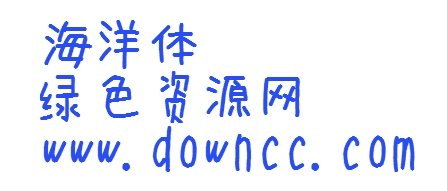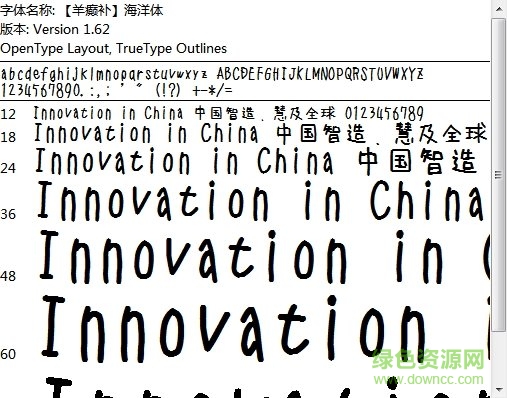
海洋體是羊癲補(bǔ)充修改的一款手寫(xiě)字體,造型上有著極其浪漫的海洋韻味,給人干凈明亮的視覺(jué)好感,打破常規(guī)端正書(shū)寫(xiě)格式,來(lái)綠色資源網(wǎng)一同體驗(yàn)吧!
海洋體帶著十分濃厚的海洋氣息,該字體濃墨重彩令人賞心悅目,整體效果瀟灑飄逸,字庫(kù)完整,可以廣泛應(yīng)用于廣告設(shè)計(jì)、宣傳海報(bào)、ppt、影視制作以及任何使用文字的領(lǐng)域!
海洋體字體是仿照兒童手寫(xiě)風(fēng)格的卡通手寫(xiě)字體,結(jié)構(gòu)帶有pop字體風(fēng)格,特別適合喜歡手機(jī)字體個(gè)性一些的朋友在手機(jī)上安裝使用。